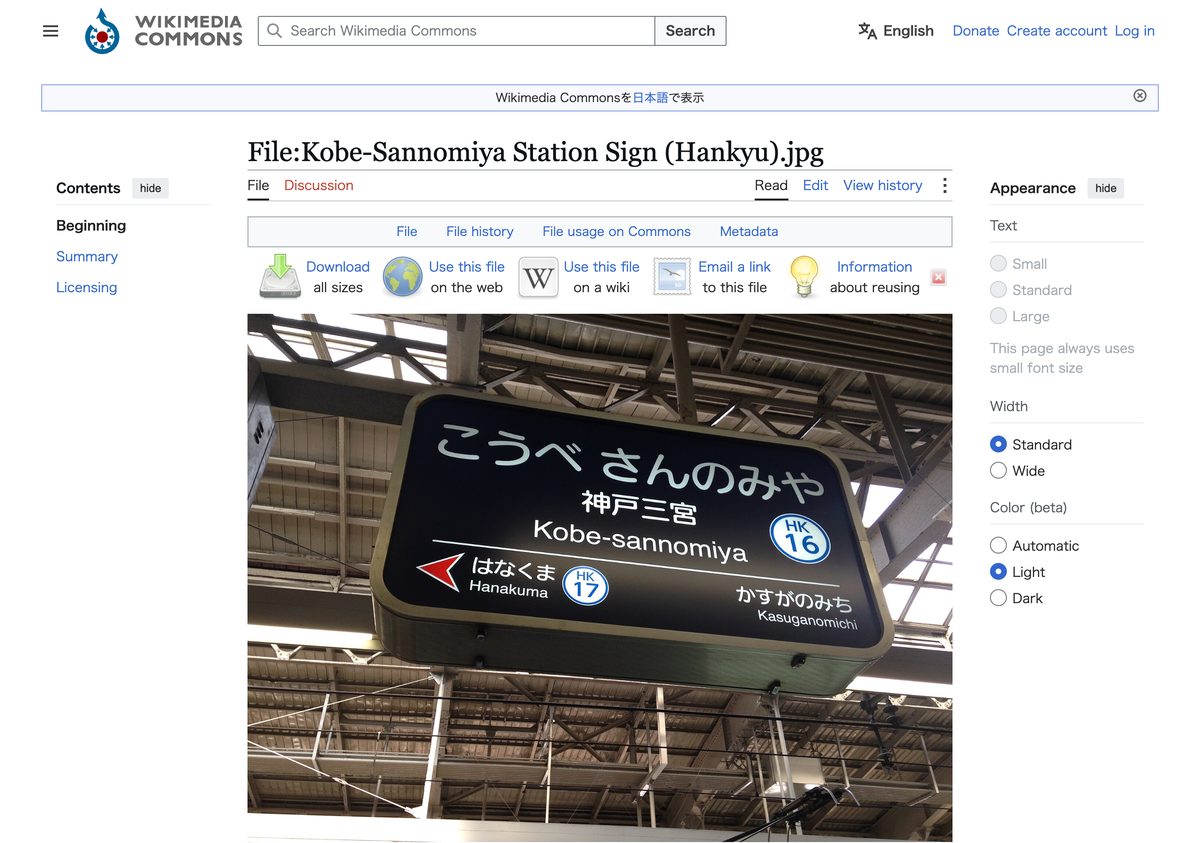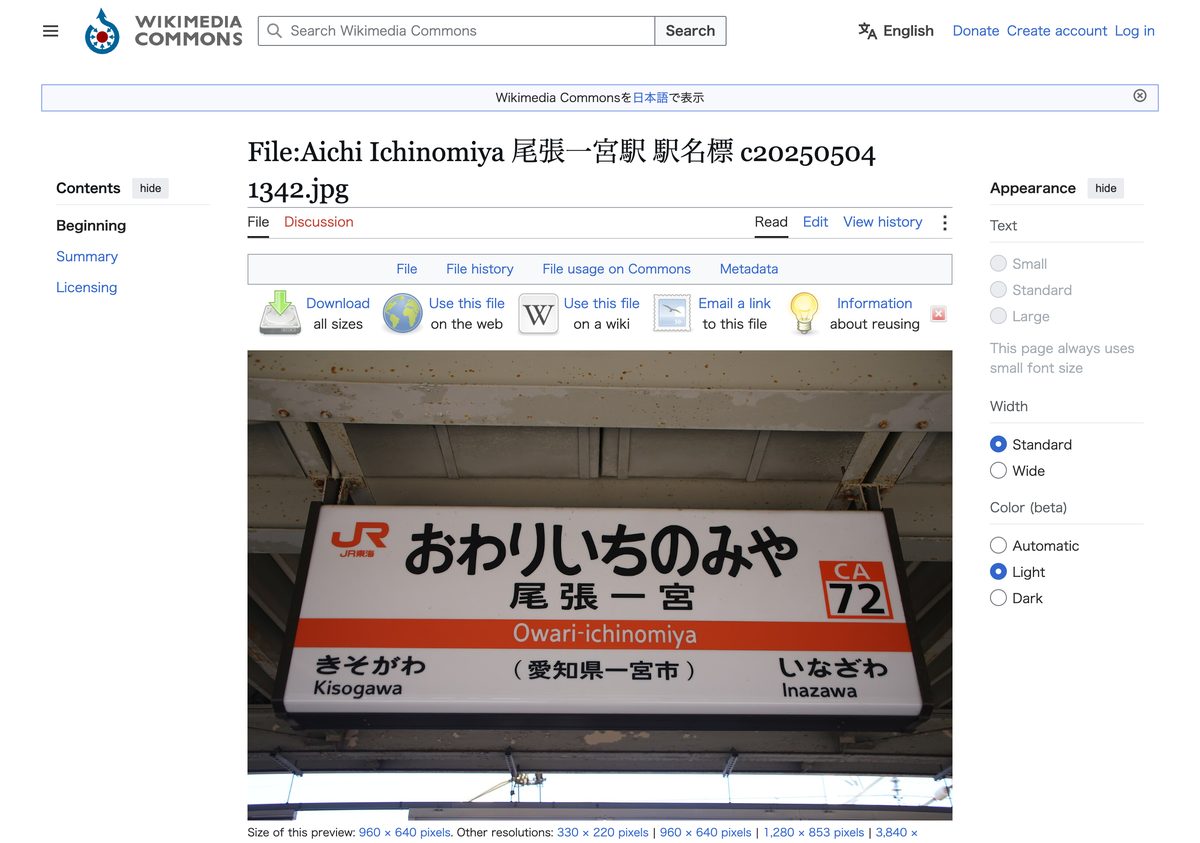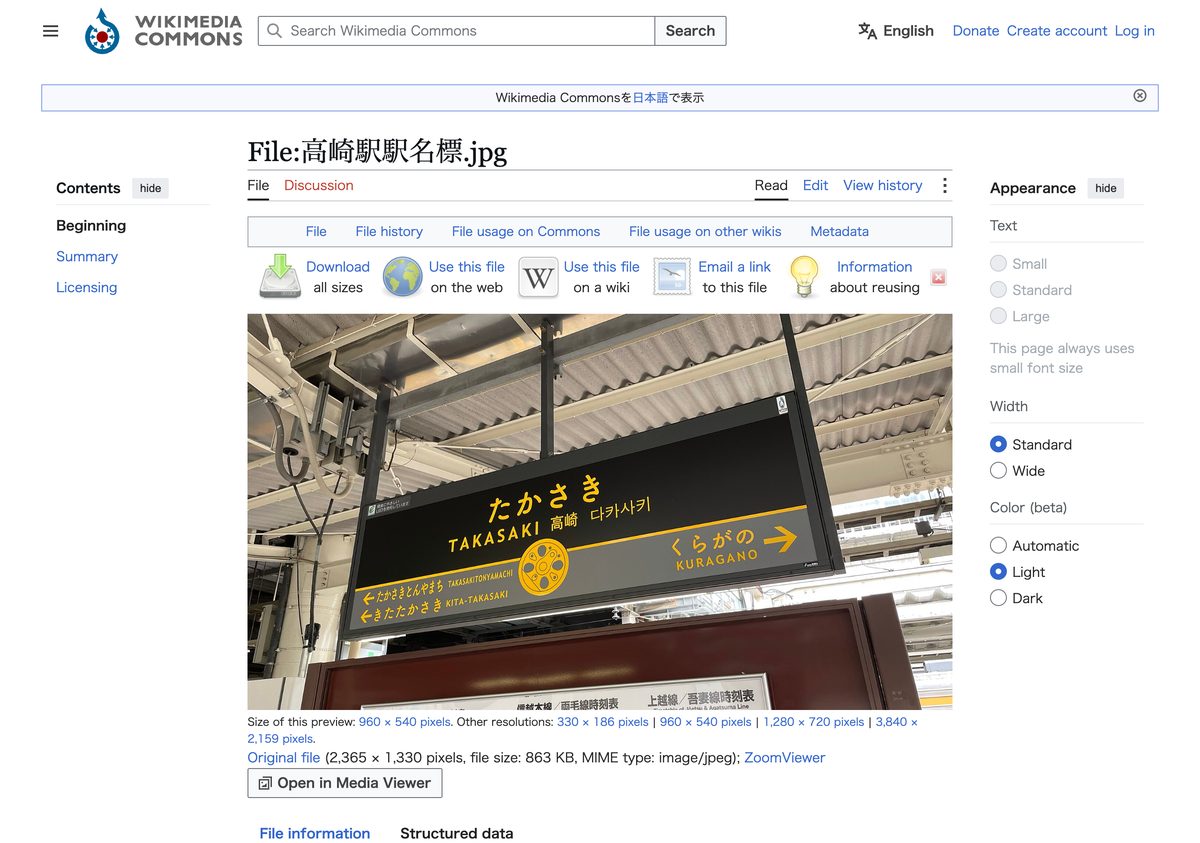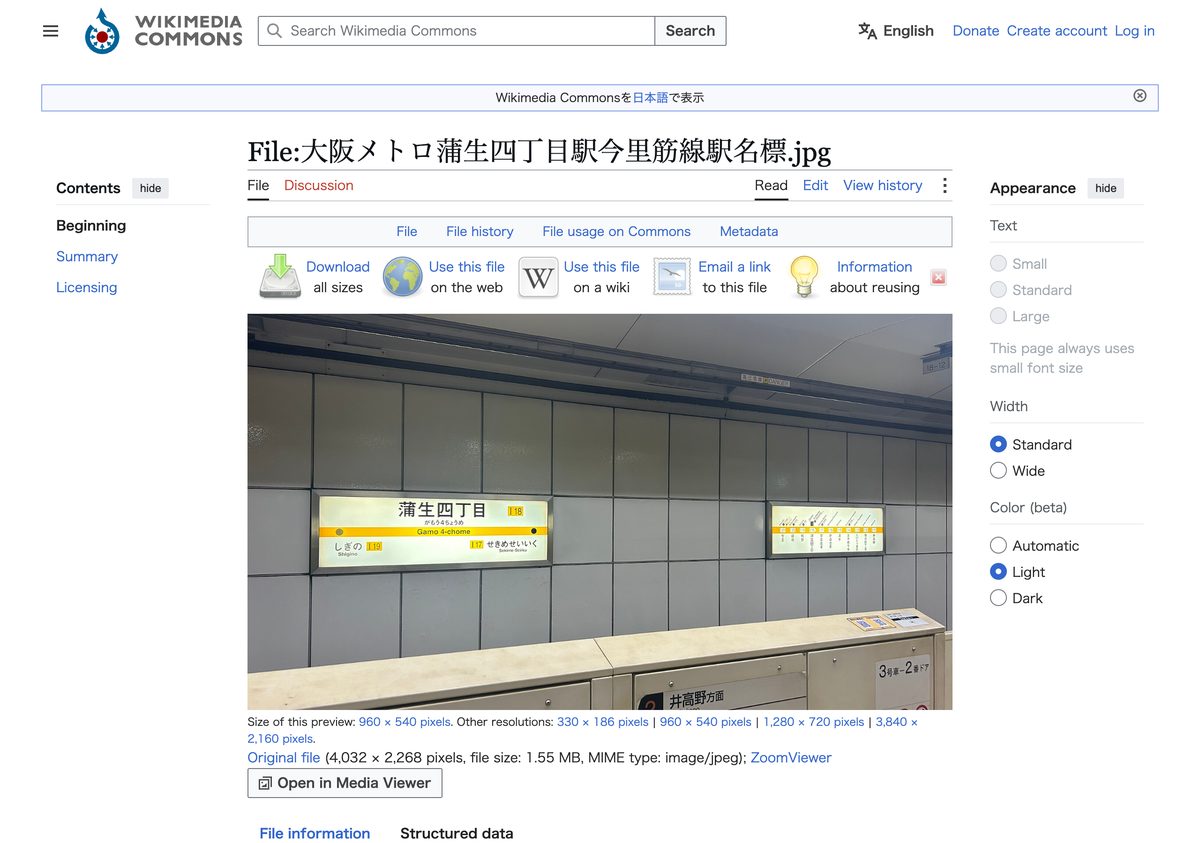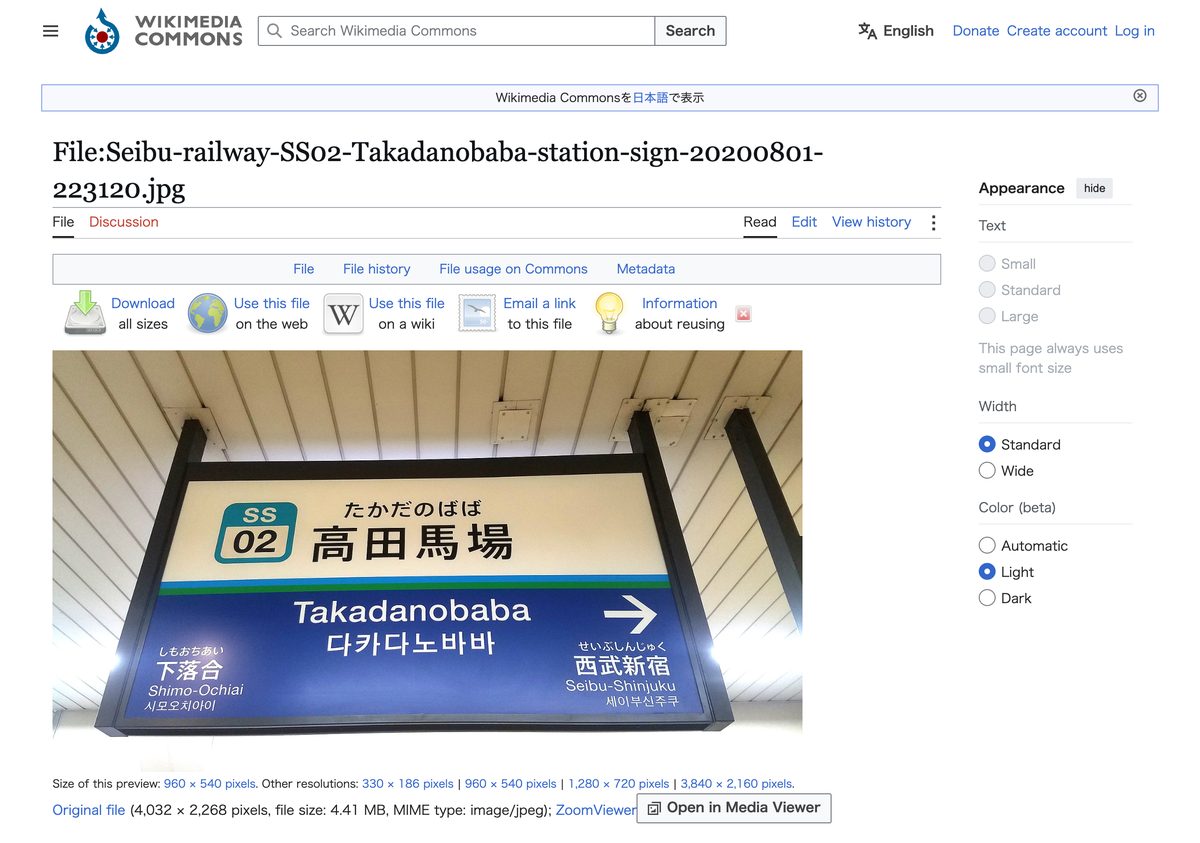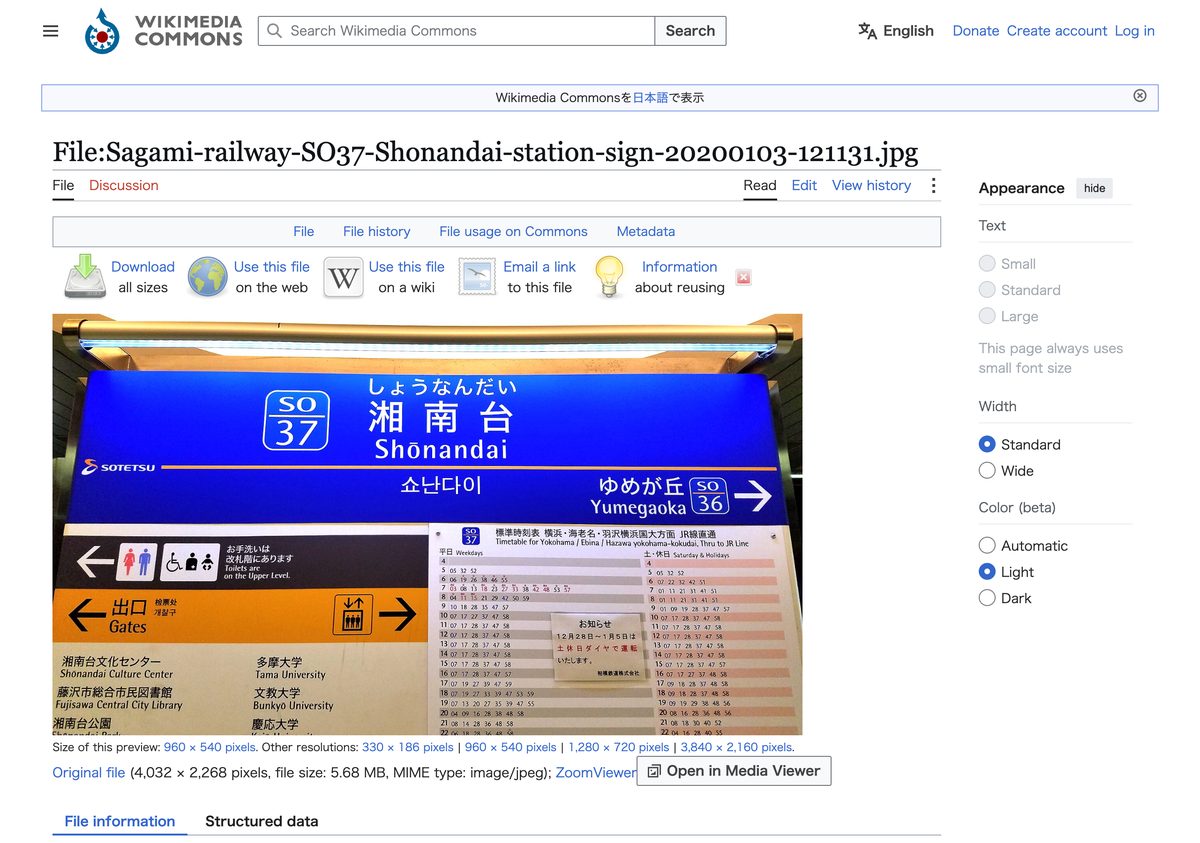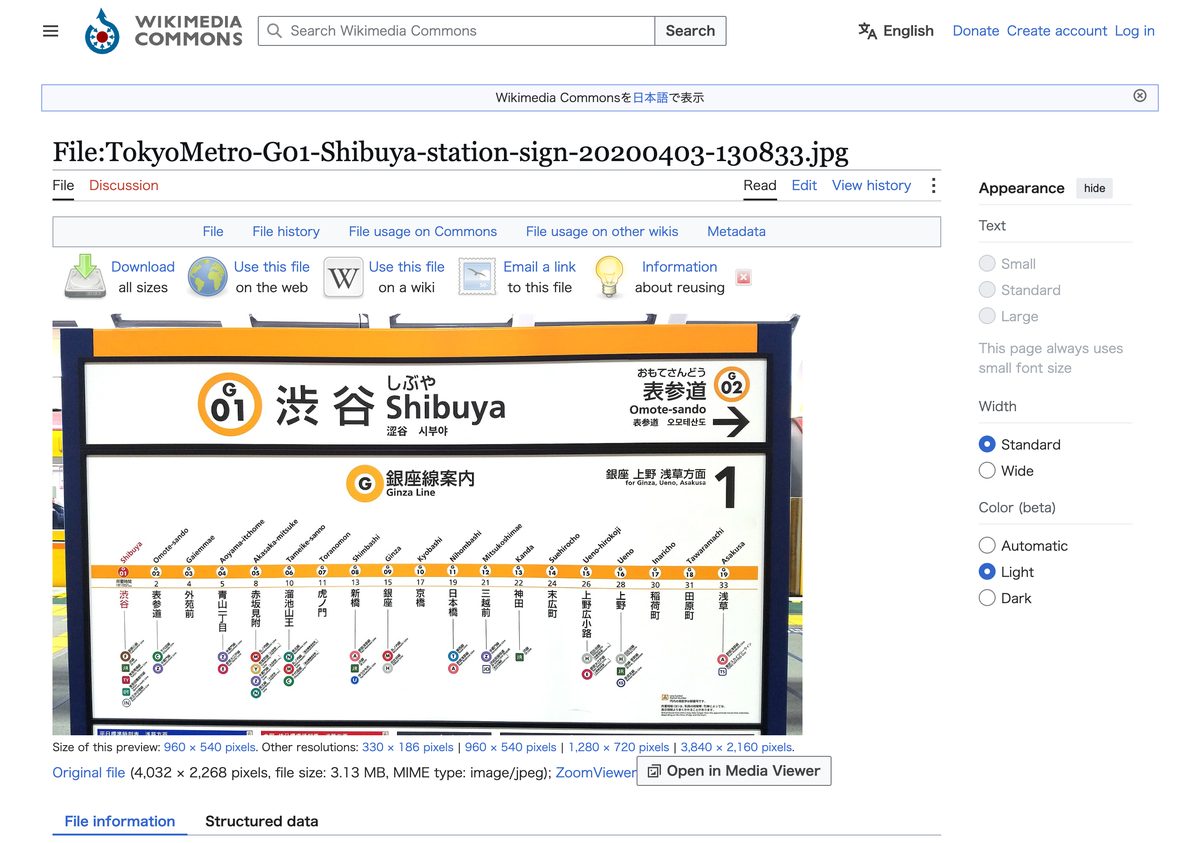
駅名標の書体
駅名標は、乗客が最も頻繁に目にしながら、ほとんど意識されない書体です。しかし各鉄道会社は、和文・欧文・駅番号という3つの要素それぞれに、視認性やブランドイメージを踏まえた書体を選んでいます。手書きの時代から写植、デジタルフォントへと移り変わる中で、その選択は会社ごとにはっきりと分かれてきました。ここでは国鉄の遺産からJR各社、東京メトロ、Osaka Metro、そして私鉄各社の駅名標書体を、出典の確度とともに集めました。
国鉄→JR東海 — すみ丸ゴシック確度B
国鉄→JR東海 — すみ丸ゴシックのロゴ使用例
1960年(昭和35年)、日本国有鉄道は「日本国有鉄道掲示規程」で掲示類の書体を統一するため、角ゴシック体の隅にわずかな丸みをつけた「すみ丸角ゴシック体(すみ丸ゴシック)」を制定しました。それまで駅の掲示は看板職人の手書きに委ねられており、書き手によって表情がまちまちだったためです。4年後に控えた新幹線開業と東京五輪を前に、「誰が書いても統一感のある文字」を目指したデザインでした。
国鉄分割民営化後、多くのJR各社は徐々にモリサワの新ゴなどデジタルフォントへ切り替えていきましたが、JR東海だけは歴代の経営陣がこの書体を評価し、東海道新幹線と在来線の駅名標に「スミ丸ゴシック体」の名で使用し続けています。手書き文化の名残が、分割民営化と技術の変遷を経た今もなお現役という点で、稀有な事例です。
JR東日本 — 新ゴ確度B
JR東日本 — 新ゴのロゴ使用例
JR東日本のサインシステムは、1990年制定の「JR東日本サインマニュアル」を土台にしています。当初は和文書体にゴナが使われていましたが、次第にモリサワの新ゴ(新ゴ B)へ移行しました。欧文はHelvetica Bold、駅番号にはFrutiger Boldという組み合わせです。国鉄時代はひらがなを大きく表示するスタイルでしたが、次第に漢字表記がメインとなり、ひらがなの比重は小さくなっていきました。
東京メトロ — 新ゴ+Frutiger確度B
東京メトロ — 新ゴ+Frutigerのロゴ使用例
東京メトロ(旧・営団地下鉄)のサインシステムは、1970年代に帝都高速度交通営団が定めた「旅客案内掲示基準」を起源とします。2004年の民営化を機にサインシステムが一新され、現在は和文に新ゴ M、欧文にFrutiger Bold、駅番号にはFutura Boldが使われています。この改定は高齢化・国際化・複雑化という3つの変化への対応が軸で、駅ナンバリングもこのタイミングで導入されました。もじ鉄による2017年時点の調査では、この書体構成が案内サインとして運用されていることが確認されています。
Osaka Metro — ヒラギノ角ゴ+Parisine確度B
Osaka Metro — ヒラギノ角ゴ+Parisineのロゴ使用例
大阪市営地下鉄(現Osaka Metro)の駅名標は、1977年の本町駅を皮切りに「ヒゲ文字」と呼ばれる独自書体から、ゴシック4550、見出しゴMB31(和文)+Helvetica(欧文)という組み合わせへと段階的に更新されてきました。転機は2015年です。御堂筋線本町駅のリニューアルを機に、和文をヒラギノUD角ゴへ、欧文をフランスのパリ地下鉄で使われる書体「Parisine(パリジーヌ)」へと切り替えました。専門メディアの調査によれば、日本の鉄道事業者がParisineを採用したのはOsaka Metroが初めてとされています。右上に路線名を大きく配置するレイアウトもこの新サインシステムから導入されました。
相鉄 — ヒラギノ角ゴ+Rotis SemiSans確度B
相鉄 — ヒラギノ角ゴ+Rotis SemiSansのロゴ使用例
相模鉄道(相鉄)は2013年から「相鉄デザインブランドアッププロジェクト」を展開し、水野学氏らをデザイン総合監修に迎えて、駅舎・車両・制服のデザインを刷新してきました。駅名標には和文にヒラギノ角ゴ、欧文には女性的で柔らかな印象のRotis SemiSans Boldが使われています。相鉄公式サイトでは、車体表示や車内掲示に「ヨーロッパの道路標識やドイツ鉄道の車体標記に使われるDIN 1451をベースにしたフォント」を採用していると説明されており、駅名標の数字部分にもDIN系のオリジナル書体が使われていると報じられています。2019年にはこの一連のデザイン刷新がグッドデザイン賞を受賞しました。
阪急電鉄 — イワタUD丸ゴシック確度B
阪急電鉄 — イワタUD丸ゴシックのロゴ使用例
関西の私鉄の中でも、阪急電鉄の駅名標は和文にイワタUD丸ゴシック M、欧文にHelvetica Regularという組み合わせが使われています。関西エリアの鉄道各社を調査した専門メディアの記事によれば、駅番号にはUD新ゴ DBが使われており、和文が丸ゴシックであるにもかかわらず駅番号だけ角ゴシックという、書体の使い分けが見られる点が特徴です。
西武鉄道 — AXIS Font確度B
西武鉄道 — AXIS Fontのロゴ使用例
西武鉄道の駅名標に使われている和文書体は、多くの鉄道会社が選ぶ新ゴやヒラギノとは異なり、AXIS Font Mです。AXIS Fontはデザイン誌『AXIS』のために開発された書体で、シャープで現代的な印象を持ちます。欧文にはHelvetica Medium、駅番号にはHelvetica Boldが使われ、和文・欧文・駅番号のすべてを一つの書体系統でまとめる会社が多い中、西武はやや異色の選択をしている事業者のひとつです。
駅ナンバリングの書体という共通言語
2004年の東京メトロ・都営地下鉄での導入を皮切りに、駅ナンバリングは全国の鉄道事業者へ広がりました。興味深いのは、駅名標の和文書体が新ゴだろうとヒラギノだろうとAXIS Fontだろうと、路線記号と駅番号にはFrutiger BoldやFutura Boldといった欧文の定番書体が選ばれる例が多いことです。JR東日本はFrutiger Bold、東京メトロと都営地下鉄はFutura Bold、京浜急行電鉄はFrutiger Boldというように、和文書体の違いを超えて、駅番号という「万国共通の記号」には視認性の高い欧文サンセリフが好まれる傾向があります。一方で阪急電鉄のようにUD新ゴを使う例や、群馬県の上信電鉄のように和文・欧文ともに丸ゴシック体のナールDで統一している例もあり、駅ナンバリングの書体一つをとっても、事業者ごとの姿勢の違いが表れています。
駅名標の書体とよく混同されるもの
駅名標の書体をめぐっては、いくつかの混同が見られます。まず、JR各社はすべて同じ書体を使っていると思われがちですが、実際にはJR東日本が新ゴ、JR西日本も新ゴを採用する一方、JR東海だけは国鉄時代のすみ丸ゴシックを使い続けており、会社ごとに方針が異なります。また、「駅名標の書体は新ゴかヒラギノのどちらか」という単純化も見られますが、西武鉄道のAXIS Fontや相鉄のRotis SemiSansのように、独自の欧文書体を組み合わせる例も少なくありません。もじ鉄(駅名標の書体を愛でる鉄道ファン)の調査は2017〜2018年時点のものであり、東京オリンピックに向けた案内サイン更新や各社のリニューアルによって、現在は異なる書体に置き換わっている駅も存在する点には注意が必要です。それでも、装飾を排し「読み違えられないこと」を目指す姿勢は、道路標識の書体と同じく、駅名標にも一貫して受け継がれています。